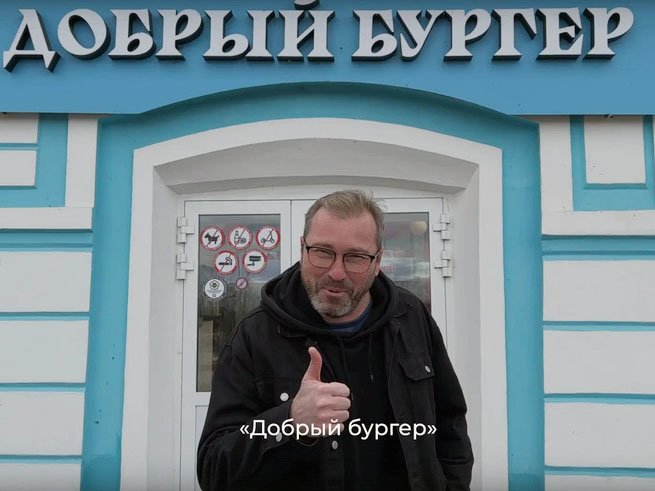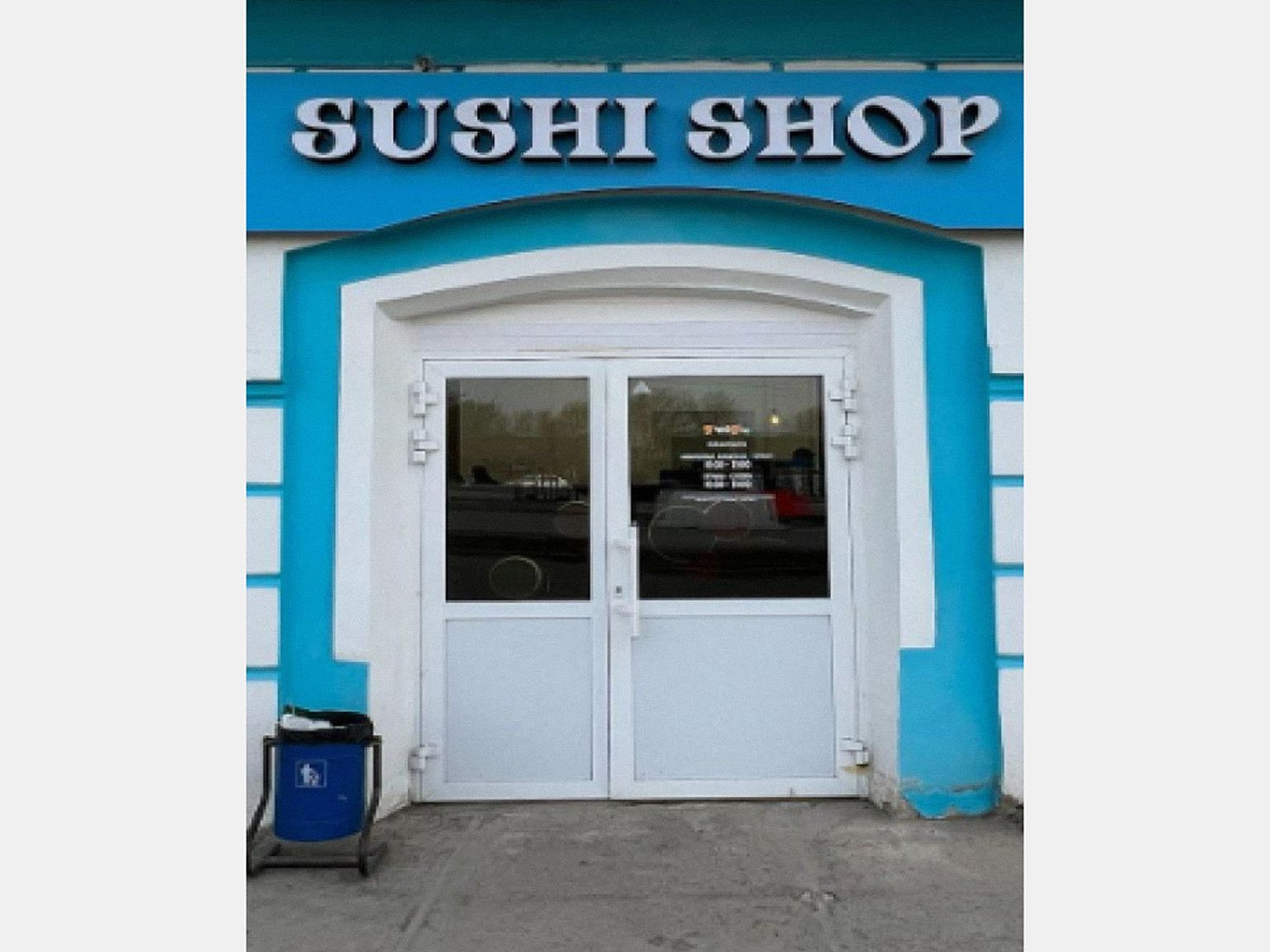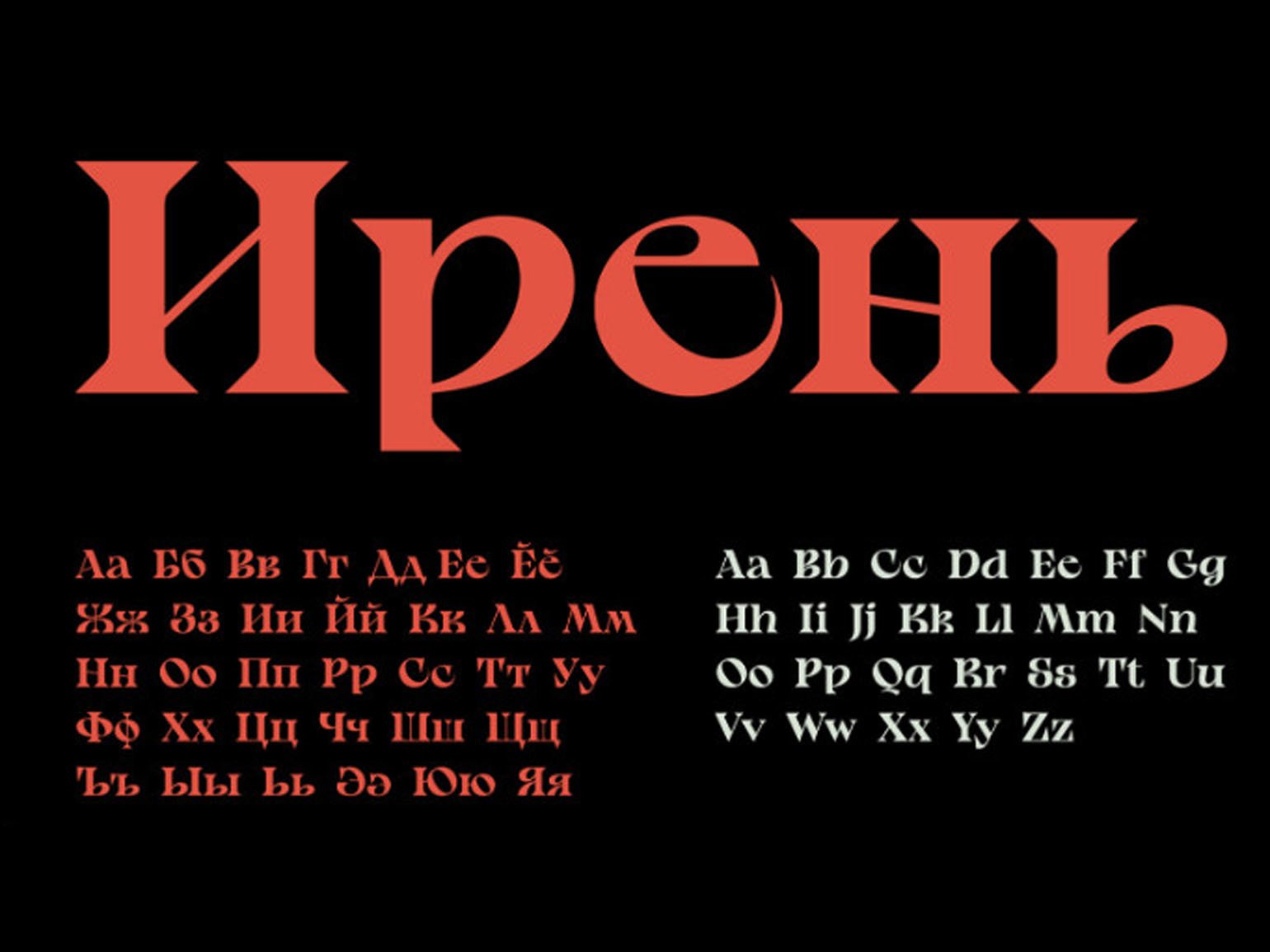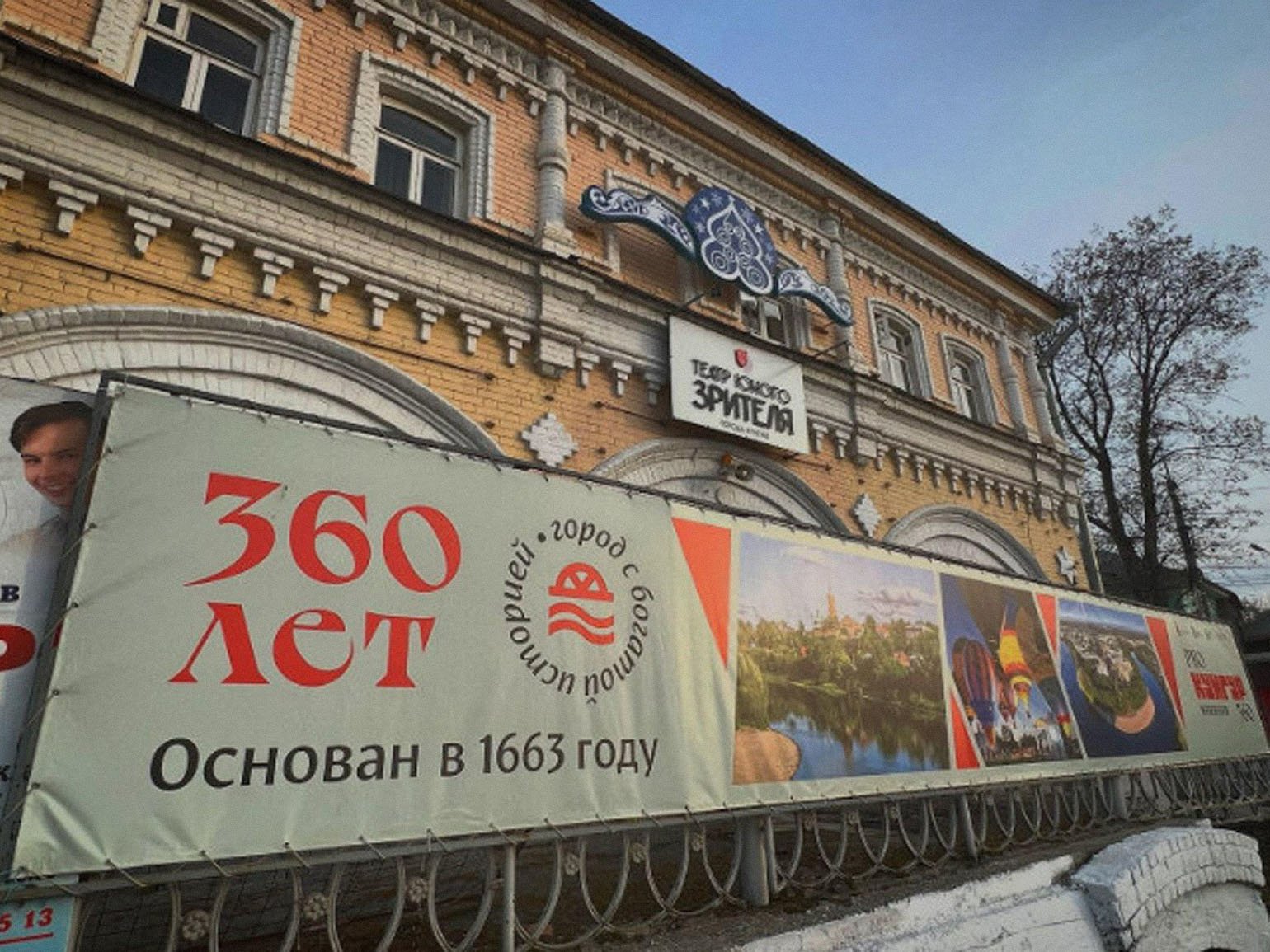
Дизайнер разработал шрифт для города Кунгура, а теперь им требуют оформлять все вывески
Получается некрасиво. Автор гарнитуры раскритиковал решение властей.
У екатеринбургского дизайнера Владислава Деревянных отец и все родственники родом из Кунгурского района, он провёл там половину детства. Сейчас Владислав — бренд-дизайн-директор рекламного агентства Voskhod Branding.
Владислав и команда архитектурного бюро «Плотинка» разработали для города Кунгура графический стиль. Его частью стал кастомный шрифт Iren Serif. Гарнитуру использовали в оформлении сувениров, детских площадок, некоторых вывесок. Потом Владислав подарил шрифт городу.
Шрифт Iren Serif
Но скоро городские депутаты приняли постановление об обязательном использовании гарнитуры на всех вывесках Кунгура. Даже надпись на английском Sushi Shop теперь оформлена в старославянском стиле. При этом шрифт вообще не предназначен для объёмных букв. Дизайнер опубликовал видео, где требует это остановить, и надеется, что огласка поможет.
Пример правильного использования шрифта
«Есть масса городов в России, где применён единый дизайн-код в оформлении вывесок, но ни один город в мире не додумался до того, чтобы использовать один шрифт для всего. Не могут ритуальные услуги и магазин детской одежды „Медвежонок“ иметь вывеску, выполненную в едином стиле одним шрифтом», — рассказал Владислав пермскому порталу 59.ru.
Пример неправильного использования шрифта